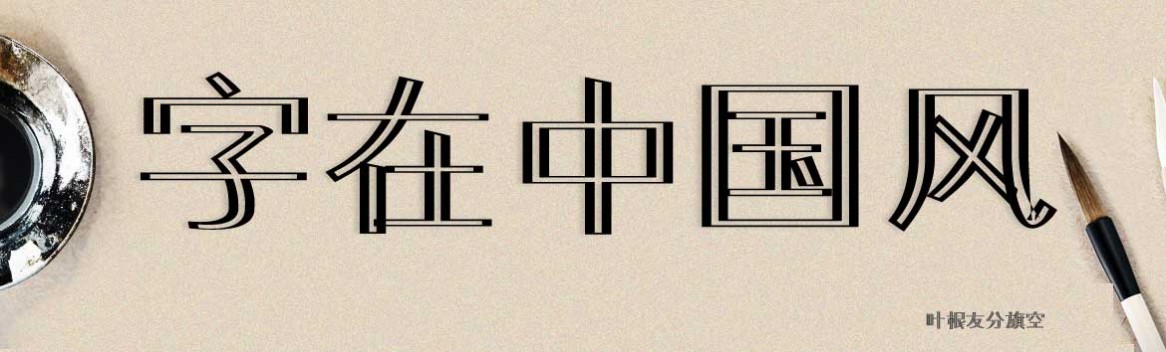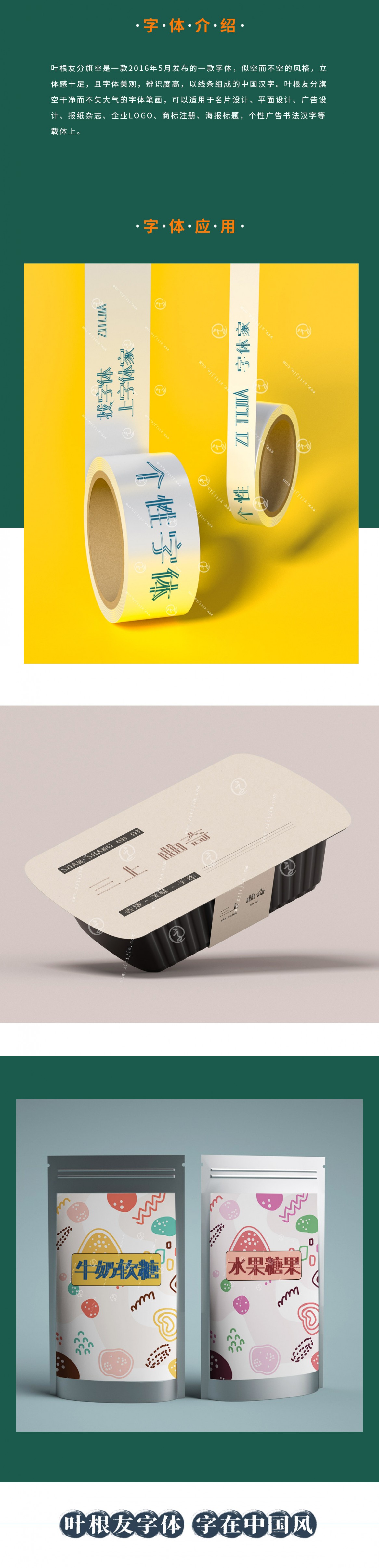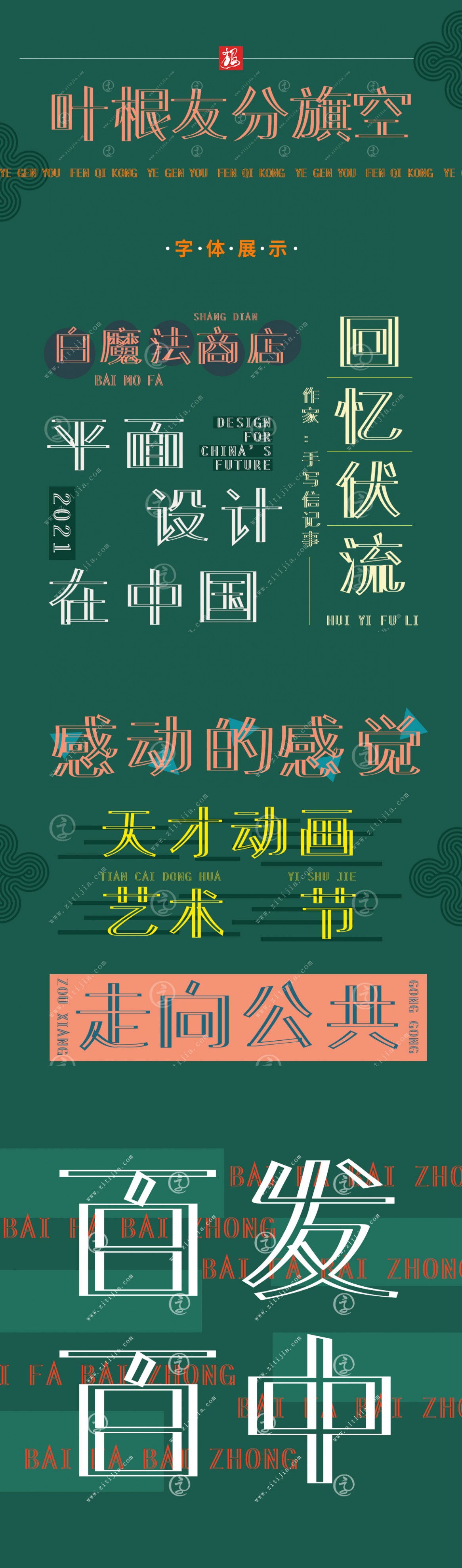
葉根友分旗空
字體作者:葉根友
創(chuàng)作年代:2016年
字體字?jǐn)?shù):6763個中文漢字以及其他英文字母和阿拉伯?dāng)?shù)字
字體介紹
葉根友分旗空是一款2016年5月新發(fā)布的一款字體,似空而不空的風(fēng)格,以線條組成的中國漢字,對現(xiàn)在黑體看多了的電腦用戶來說是一種新鮮的感覺,我們可以用更新的思維來探索中國漢字字體的發(fā)展,而不局限橫豎撇捺的方正平劃,葉根友分旗空適用于各類海報標(biāo)題,個性廣告書法漢字等載體上,具體怎么用還是看各位看官心中美感了。